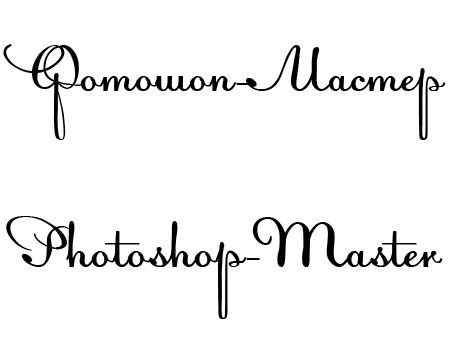
хороший шрифт...)
он подходит под русский?
Очень красивый шрифт!
аккуратный и очень красивый. спасибочки ^^
Спасибо:)) Супер Шрифт :))
красивый шрифт!
Классный шрифт)
ооо... прям мой подчерк=)
шрифт крутооой)
шрифт во многом пригодился)
Спасибо! Шрифт - то, что нужно!